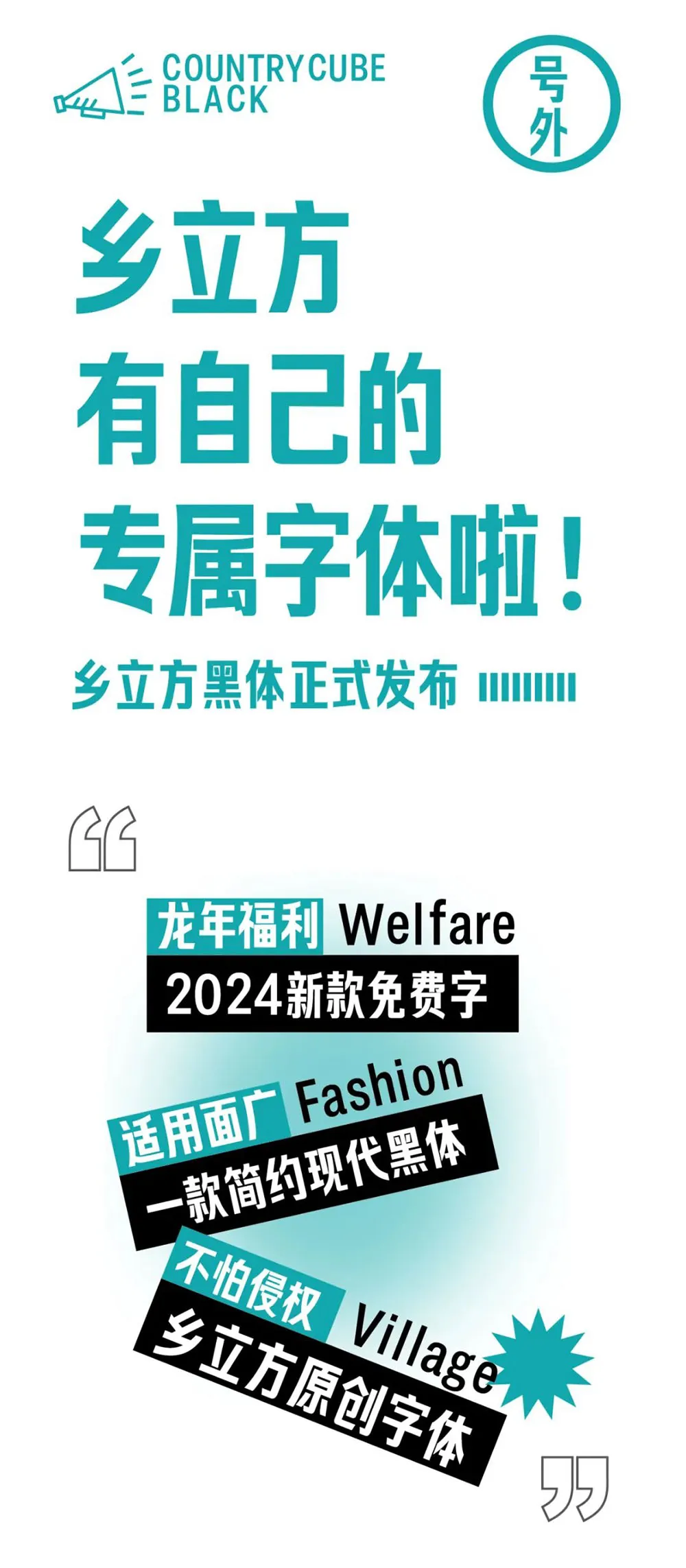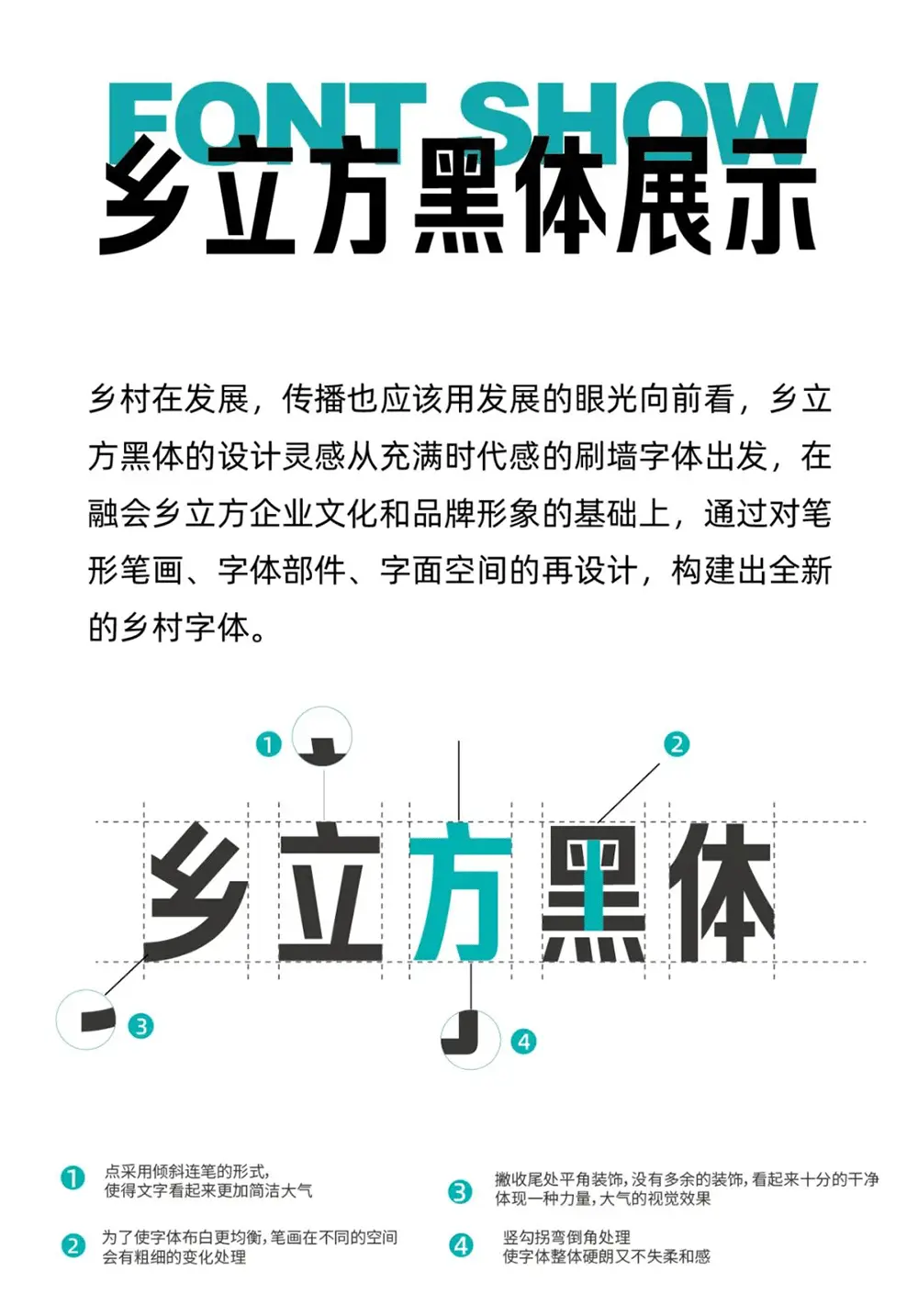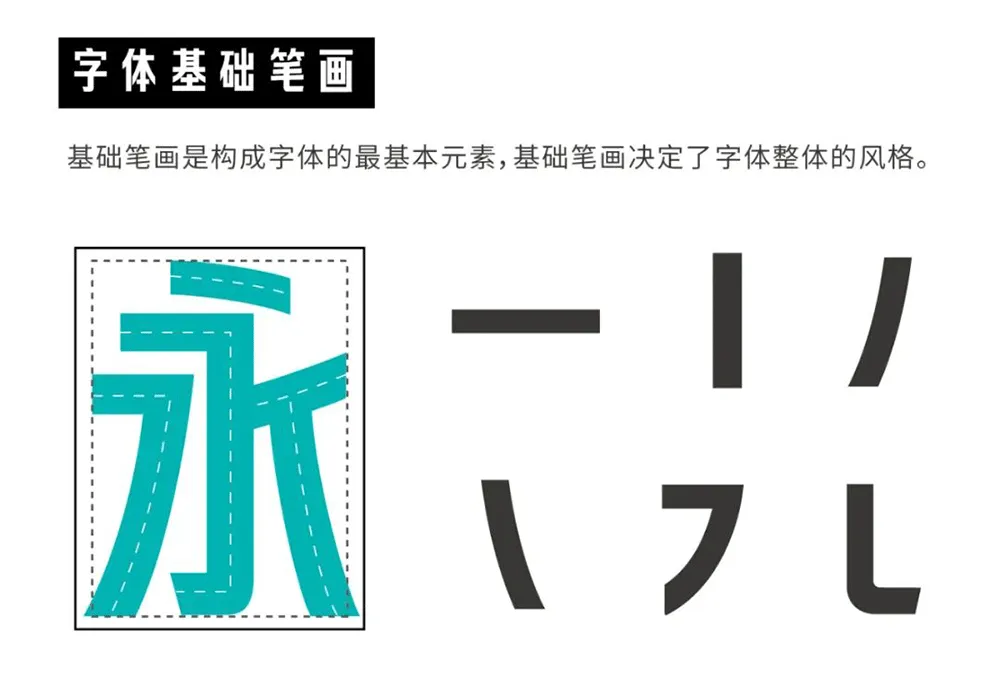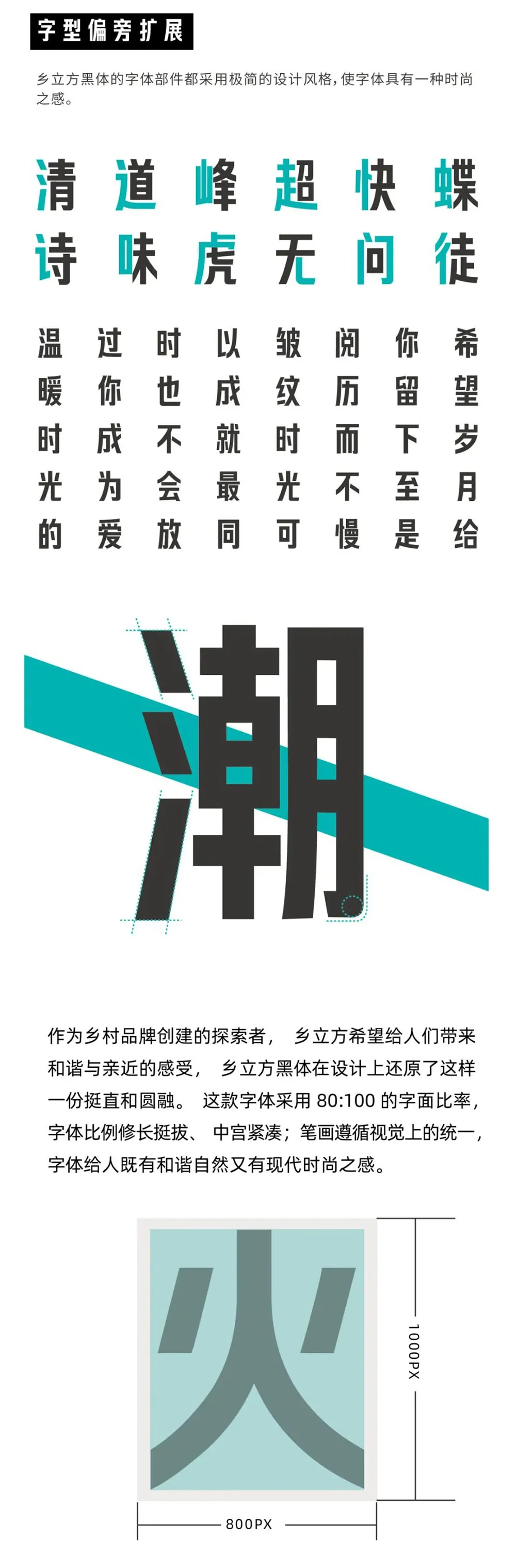
我是鄉立方黑體,由火石品牌字體團隊為鄉立方量身定製,以字為媒,繪鄉村風情,傳品牌溫度。
鄉立方字體設計團隊秉承服務大眾的原則,致力於打造一款既實用又廣泛適用的字體,希望它能被廣泛應用於各行各業,真正做到字體好用,適用面廣,實現字體使用便捷、應用場景豐富多樣,無論在哪種傳播媒介中都能展現出卓越的效果。
鄉立方黑體總共囊括了4500個基礎常用字,可覆蓋日常98%的使用範圍,未來,我們將根據實際情況逐步補充和完善字庫。